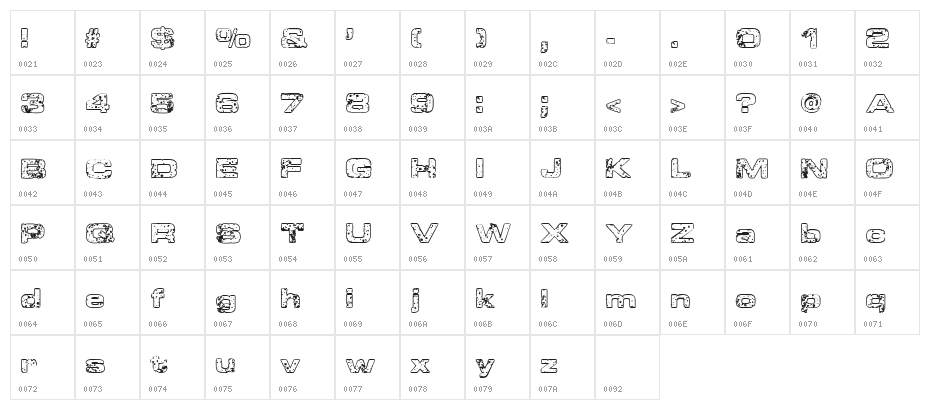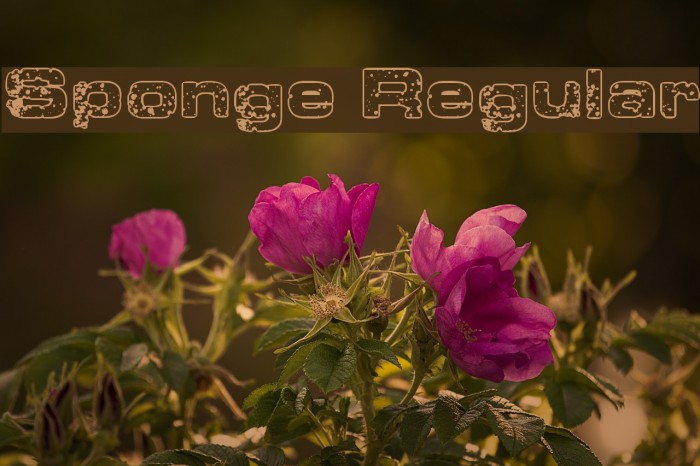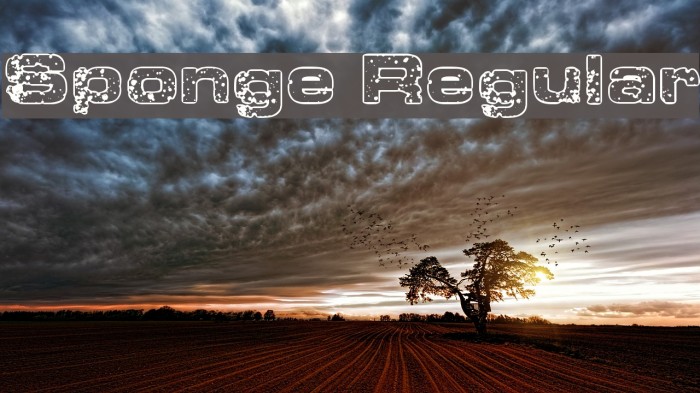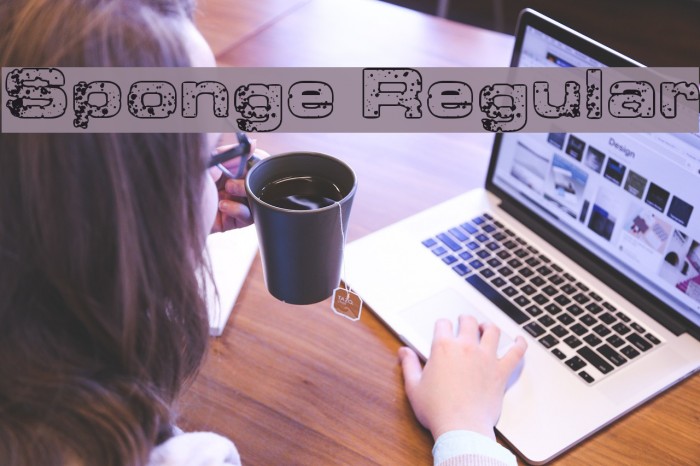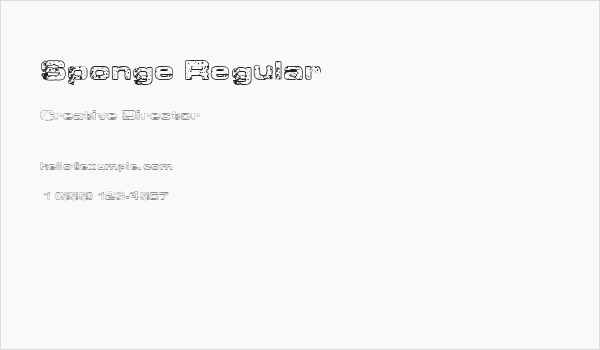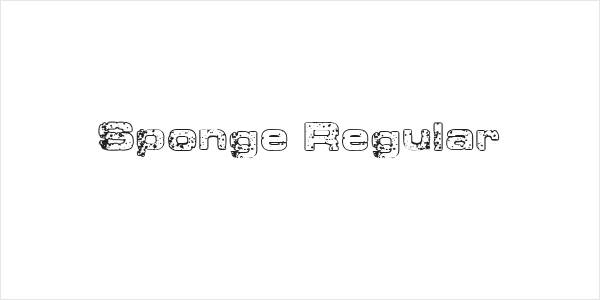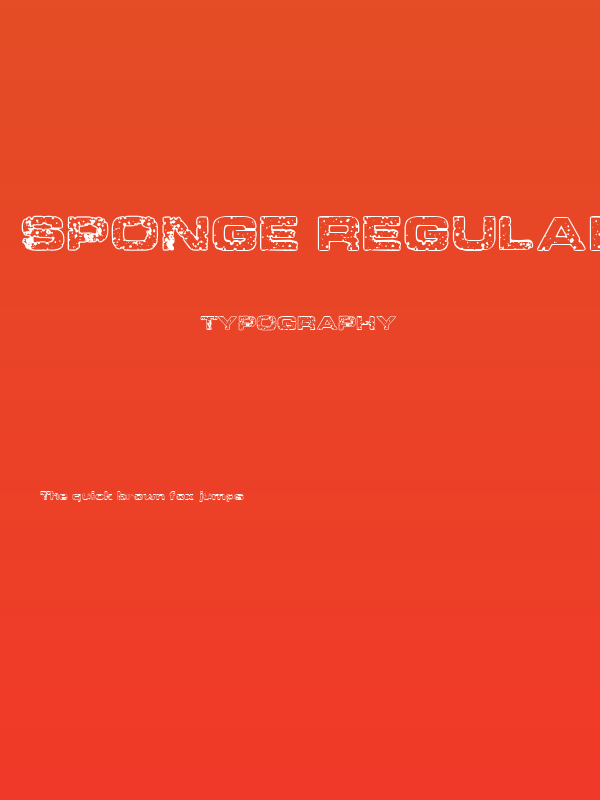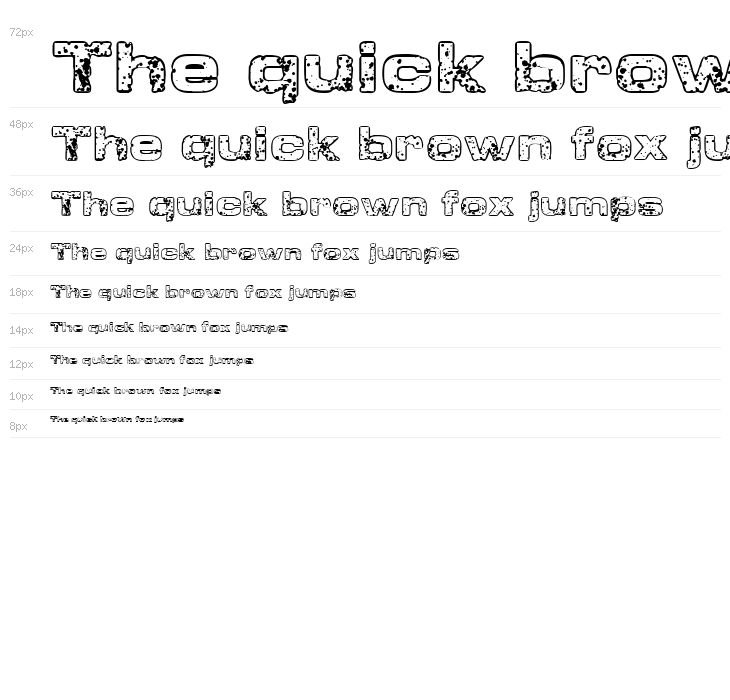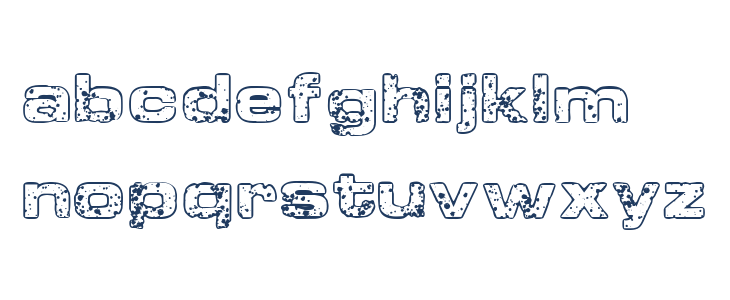
Sponge Regular Font
✎ Distorted Eroded
| Proyectos propuestos | Ideal for posters, album covers, branding, and any project needing a bold, textured look. |